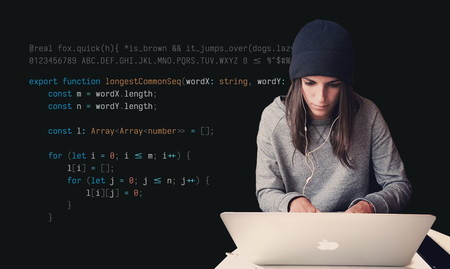
Las cinco mejores tipografías open source para tu editor de código y tu terminal
Cuando nos pasamos muchas horas frente a una pantalla, nos gusta poder disponer de una tipografía fácil y agradable de leer. Por comodidad o desconocimiento, muchas veces nos conformamos con las tipografías monoespaciadas que nuestro sistema operativo incluye por defecto... pero pueden no ser la mejor opción.
Si además, la mayor parte de ese tiempo lo pasamos escribiendo código (o peor, revisándolo), es habitual que busquemos una tipografía de referencia, para no vernos obligados a 'hacer' la vista a una nueva cada vez que cambiamos de aplicación.
De modo que hemos preparado una breve selección de las 5 tipografías monoespaciadas 'open source' que te recomendamos para usar en la terminal o a la hora de picar código:
Fira Code
Fira Code Ejemplos de ligaduras de programación, bajo el nombre de la tipografía.
Fira Code es una tipografía desarrollada por Mozilla (a partir de Fira Mono) y que podemos encontrar, por ejemplo, en los proyectos de JetBrains (los creadores de IntelliJ y Kotlin).
Posiblemente uno de de los tipos de letra más populares entre los programadores gracias a su amplia gama de ligaduras, y a detalles como la puntuación dependiente del contexto.
Las ligaduras de programación son un recurso que permite, por ejemplo, mostrar el operador '->' como un único carácter (una flecha), ahorrándoles unos pequeñas milésimas de segundo a nuestras ojos y cerebros mientras leemos el código.
Esta tipografía, que destaca también por su amplio soporte para símbolos ASCII y matemáticos, está igualmente disponible en repositorios Linux y, como la anterior, con un nombre que varía según la distribución: font-firacode, fira-code-fonts, ort-fira-code...
Cascadia Code
Hace un año, durante su penúltimo evento Build, Microsoft anunció el lanzamiento de una tipografía 'open source' específicamente diseñada para ser usada en editores de código y terminales de línea de comandos: Cascadia Code.
De hecho, la idea era que llegara a muchos ordenadores de la mano de Windows Terminal, software al que acompañaba y homenajeaba (el nombre en clave del mismo antes de ser presentado fue, precisamente, Cascadia).
Por supuesto, Cascadia incluye las famosas ligaduras:
"Las ligaduras de programación son más útiles cuando se escribe código, ya que crean nuevos glifos combinando caracteres. Esto ayuda a que el código sea más legible y fácil de usar para algunas personas".
Iosevka
Más que una tipografía, Iosevka es una familia de las mismas: 15 variantes, cada una de ellas desdobladas en la modalidad sans serif y slab serif, y con sus correspondientes formatos normal, negrita, cursiva y negrita-cursiva. Una amplia gama de opciones la de estas tipografías open source.
Dos de las variantes, Iosevka Term y Iosevka Fixed están especialmente optimizadas para su uso en emuladores de terminal, según explica su página web oficial. En el caso de esta última variante, "las ligaduras se desactivan para garantizar una mejor compatibilidad en ciertos entornos".
Otras tres variantes (Iosevka Aile, Iosevka Etoile y Iosevka Sparkle) no son monoespaciadas sino 'cuasi-proporcionales' y están optimizadas para escritura y documentación técnica.
La misma web ofrece más datos sobre la tipografía: 6391 glifos incluidos (cada uno de exactamente 1/2 em de ancho), 159 idiomas soportados, 15 clases de ligaduras, etc.
Hack / Hæck
Hack es una familia de tipografías 'open source', disponible en sus cuatro variaciones (normal, negrita, cursiva y negrita-cursiva) diseñada con el objetivo de optimizar su legibilidad en pantalla, incluso a tamaños de texto pequeños.
Otro de los objetivos planteados por sus creadores fue el de ofrecer compatibilidad en un gran número de idiomas, por lo que incluye 1500 glifos de alfabetos basados en el latino, el griego y el cirílico.
Haeck Modalidad 'Hæck', dotada de ligaduras.
Su código está disponible en Github, y su licencia 'open source' es muy permisiva y permite desde la modificación al uso comercial. Gracias a ello existe una versión de Hack llamada "Hæck", que se caracteriza por incluir ligaduras.
Inconsolata
Inconsolata es una tipografía 'open source' que no sólo es muy legible en pantalla, sino que -al contrario que otras de esta clase- sigue siendo igual de legible cuando pasa a estar impresa en papel.
Incluye ligaduras de programación para algunos de los operadores más habituales, y -según explica su autor- copia de tipografías japonesas el uso de 'microserifas' para aumentar la nitidez del resultado final.
Cuenta con una variante experimental (desarrollada poR el mismo creador que la original) que incorpora comillas rectas y a la que se conoce como InconsolataGo.